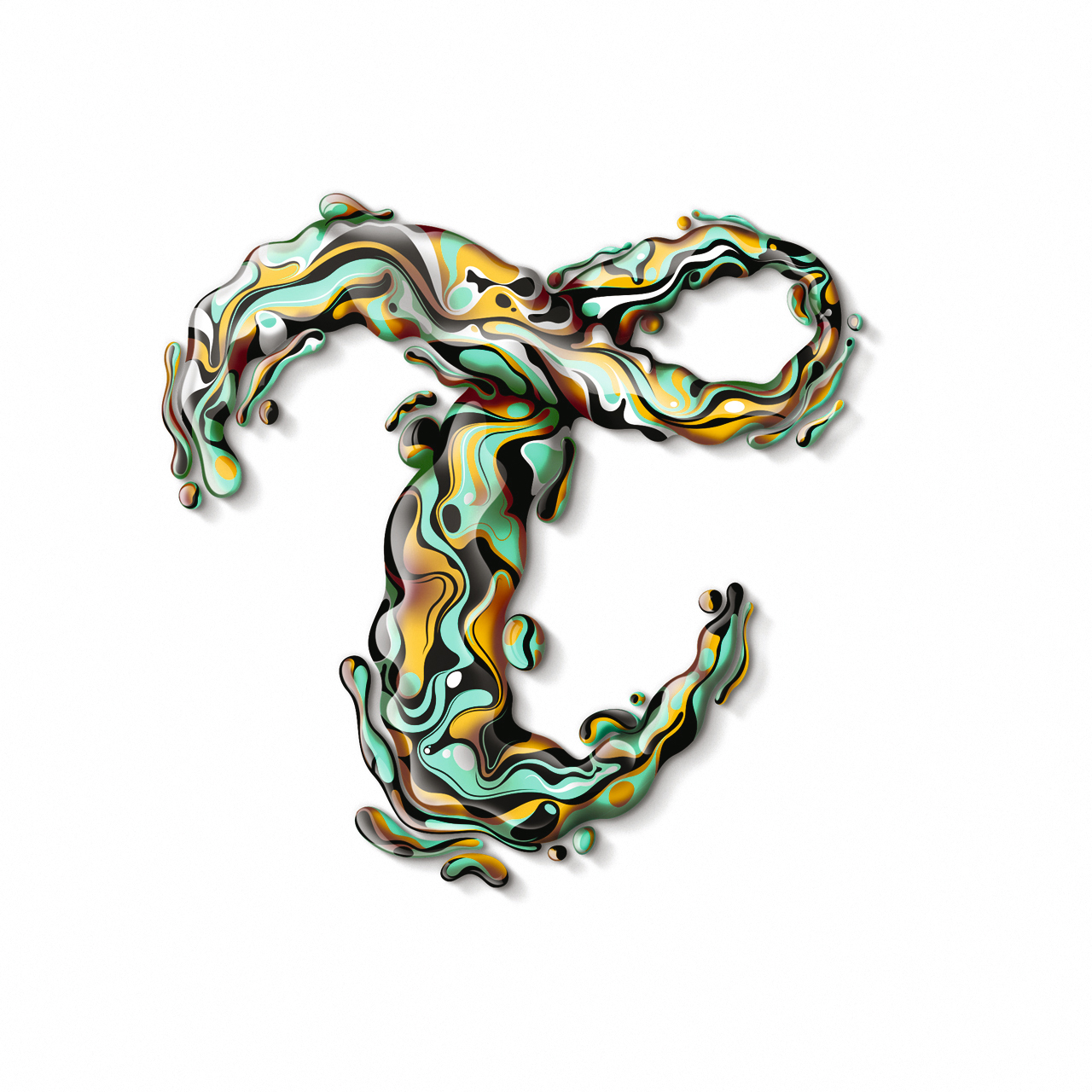
‘서체가 있는 36일(36 Days of Type)’ 프로젝트
개인 프로젝트가 꾸준히 상승세를 보이고 있는데, 스스로 동기를 부여하는 것이 최선의 영감으로 이어질 수 있다는 점을 증명하는 셈이다. 하지만 니나 산스와 라파 고이코에체하는 ‘서체가 있는 36일’ 모험을 통해 조금 다른 것을 시도해 보기를 원했다.
‘서체가 있는 36일(36 Days of Type)’ 프로젝트
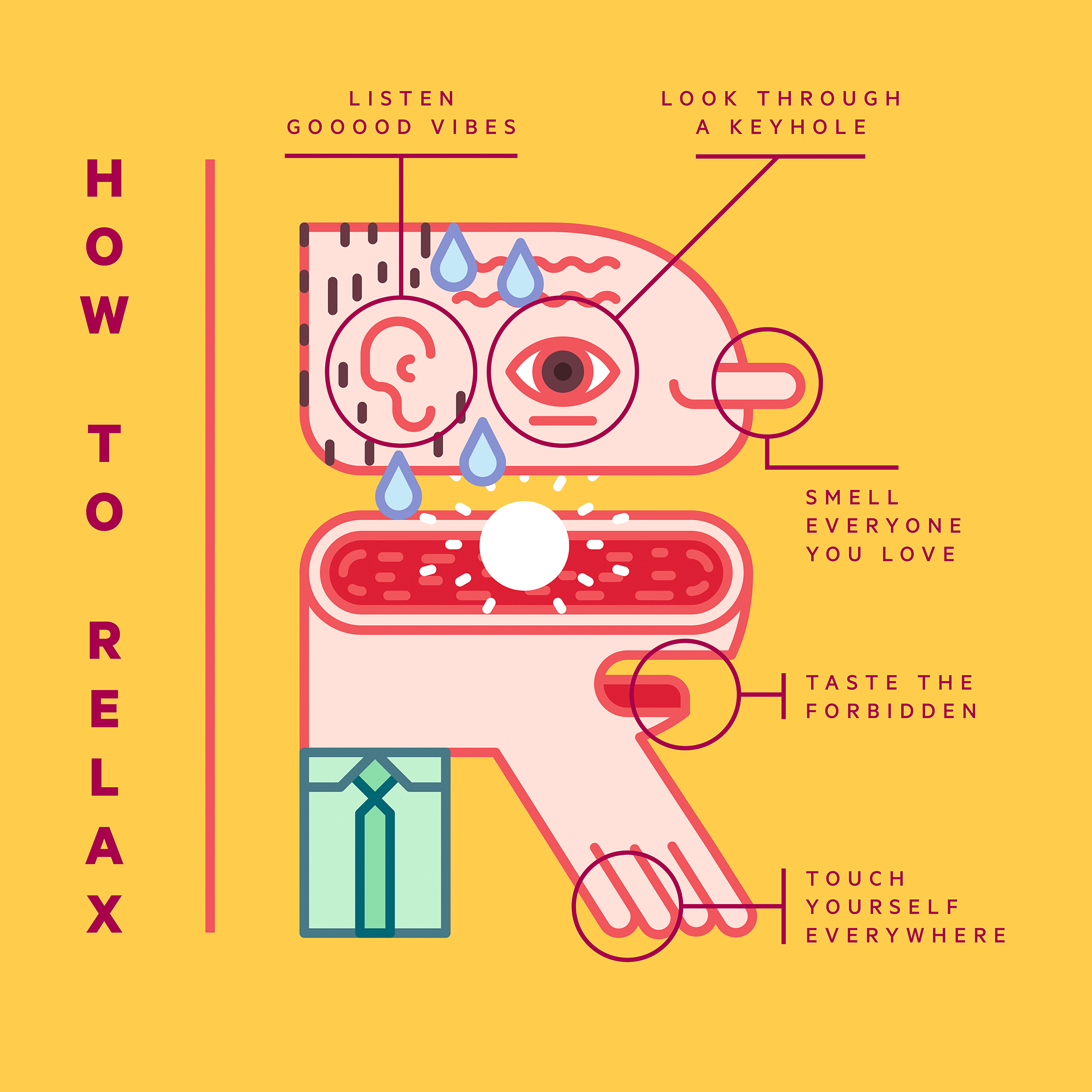
개인 프로젝트가 꾸준히 상승세를 보이고 있는데, 스스로 동기를 부여하는 것이 최선의 영감으로 이어질 수 있다는 점을 증명하는 셈이다. 하지만 니나 산스와 라파 고이코에체하는 ‘서체가 있는 36일’ 모험을 통해 조금 다른 것을 시도해 보기를 원했다.
“우리는 개인적 과제보다는 더욱 세계적인 것에 도전하고 싶었습니다. 되도록 많은 사람을 초빙해 그들의 서체 디자인과 레터링 기술을 보여주고 싶었죠. 이를 통해 그래픽 표현의 가능성을 탐구하고자 했습니다. 끝이 없는 그래픽 표현의 가능성을 서체와 그 형태로 보여주는 것이 우리의 발상이었습니다.”
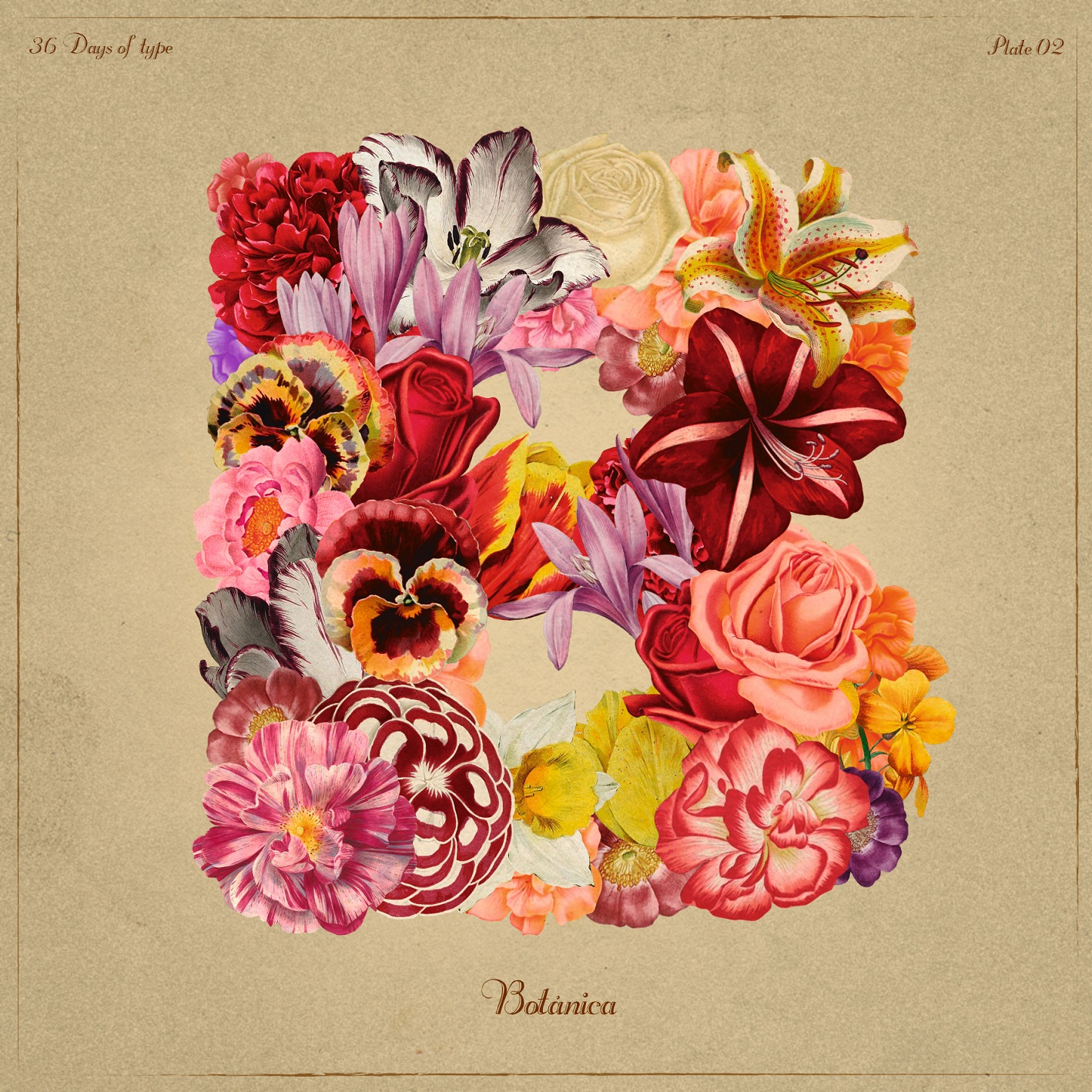
이들은 우호적인 분위기를 유지하면서 24시간 동안 그들에게 제출된 모든 작업을 확인해야했다. 그들의 ‘서체가 있는 36일’ 인스타그램 계정에 선보일 각각의 문자를 최종적으로 고르는 것이다.
“우리가 이 프로젝트를 하면서 가장 좋았던 점은 위대한 아티스트들과 다양한 사람들을 만날 수 있었던 것이었습니다. 정말 큰 영감을 주는 작품들이 많았으며 여러 사랑스러운 사람들을 만날 기회가 있었습니다. 이러한 공동체가 자라나며 시너지 효과를 내는 것을 보니 정말 행복했습니다.”
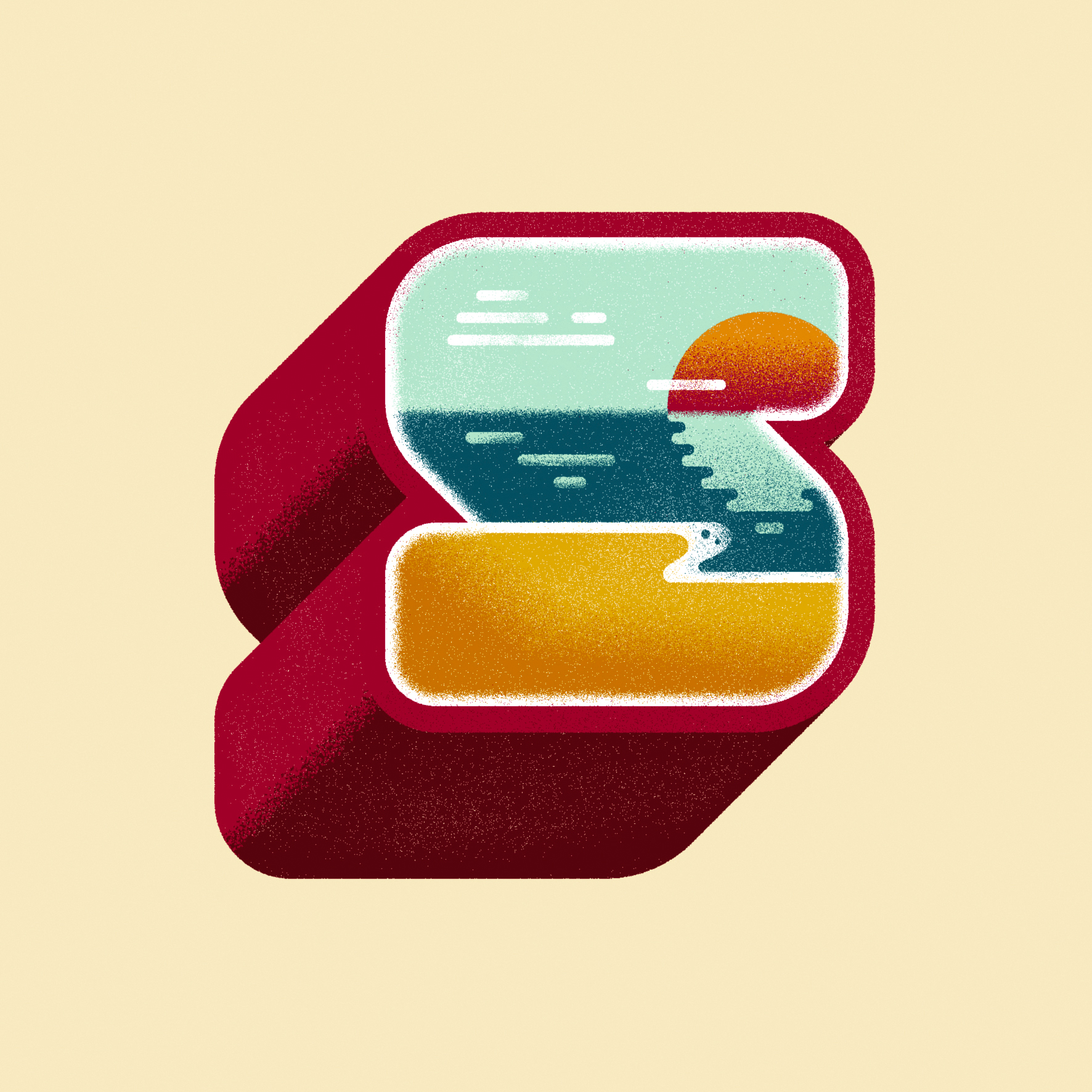
-Project by 니나 산스 & 라파 고이코에체아(NINA SANS & RAFA GOICOECHEA)